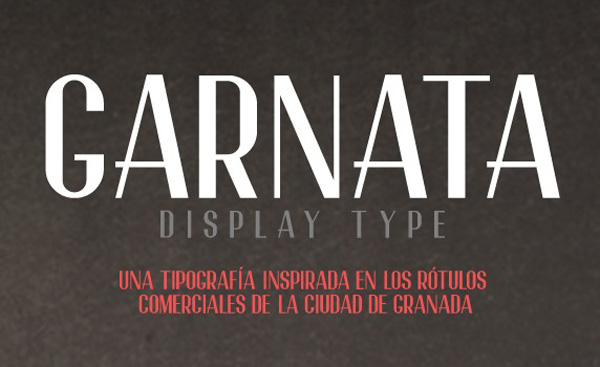
Vieeeeeeernes, y con él la tipografía de la semana que esta vez viene de aquí cerquita, de la parte sur del país, de Andalucía. Para ser concretos de Granada. Según las palabras de sus autores, inspirada en los rótulos de la ciudad española. Sus tres autores, con sus respectivos portfolios son Juanjo Rivas y Nano Torres para la tipografía, y Rafa Galeano en el proyecto de animación. La tipo viene bajo licencia Creative Commons. Aquí os la dejo! Espero que os guste y recordad que los like y los follow ayudan mucho así que visitadnos en Twitter y Facebook. También nos podéis encontrar en Flipboard buscando nuestra revista El Arquitecto de Ilusiones.